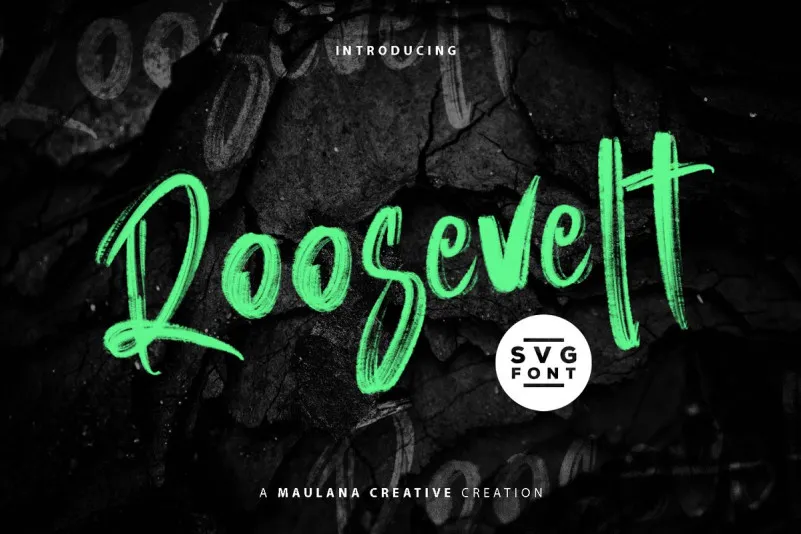
Roosevelt SVG Brush Font – Download Grátis
A M.0Type apresenta a Roosevelt Brush Font, uma opção gratuita para designers buscando adicionar um toque autêntico e sofisticado a seus projetos digitais. Esta fonte é perfeitamente adequada para grunge ou projetos de arte criativos, fornecendo uma aparência rústica que pode ser usada em um amplo espectro de aplicativos design. Seja para criar assinaturas elegantes, embalagens de produto, capas de livros, logotipos, desenhos gráficos ou até mesmo materiais publicitários, Roosevelt Brush Font é uma escolha perfeita. Sujeito à sua criatividade e ao estilo que deseja aplicar às suas criações, Roosevelt Brush Font adicionará um toque de autenticidade única a qualquer projeto. Com seu design cuidadosamente cuidado e detalhado, Roosevelt Brush Font é a fonte certa para designers buscando dar vida aos seus projetos digitais.